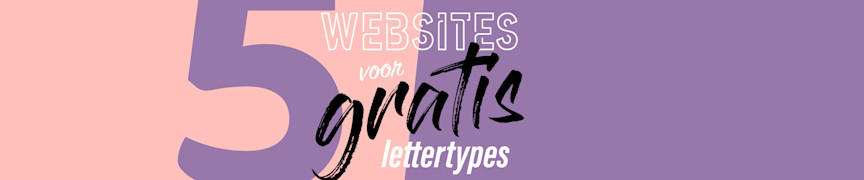
De vijf beste websites voor gratis fonts
Organiseer je een feest? Verkoop je een nieuw product? Heb je een knallende actie? Dan kunnen opvallende flyers of posters niet ontbreken. Terugkerend element op bijna elk stukje drukwerk is je lettertype. Daarom laten wij je in dit blog zien waar je de beste gratis fonts vandaan haalt.
Een font is net zo persoonlijk als je huisstijl of boodschap. Geef de keuze van een lettertype daarom net zoveel aandacht als de rest van je ontwerpproces.
Dafont.com
321-5xgratisfonts-dafont-featured Het fontwalhalla voor designers. Op moment van schrijven telt deze site maar liefst 34.472 fonts, in negen verschillende hoofdcategorieën. Allemaal gratis! Of je nou zoekt naar een nieuw font voor je website of een lettertype voor een nieuwe tattoo, er zit iets voor je tussen.
Google.com/fonts
321-5xgratisfonts-Googlefonts-featured Google is je vriend. Zoekt en gij zult vinden is kinderspel voor Google, ook voor je gratis fonts. Deze site is vooral handig voor webdesigners. De meeste fonts die je hier downloadt zijn web-proof.
Fontsquirrel.com
321-5xgratisfonts-FontSquirrel-featured Fontsquirrel is het schattige broertje van Dafont.com. Je kan er alleen iets meer doen dan alleen fonts downloaden. Op Fontsquirrel vind je een uitgebreid blog, een forum waar mensen elkaar helpen de juiste fonts te vinden en zelfs een font identifier.
Losttype.com
321-5xgratisfonts-Losttype-featured De verloren pareltjes onder de fonts vind je hier terug. Losttype publiceert niet vaak iets, maar als ze het doen plaatsen ze fantastische fonts. Mooie scriptfonts en eigentijds kleurgebruik, lekker van nu! Frisse fonts voor je meesterlijke menukaart of lekkere lettertypes voor op een T-shirt.
Behance.com
321-5xgratisfonts-Behance-featured Hét designersplatform! Een soort wereldwijd archief aan designerportfolio’s. Van fotografie tot aan ontwerpen voor woonhuizen, je vindt het allemaal op Behance.com. Fonts dus ook. Typ in de zoekbalk wat je nodig hebt en je vindt fantastisch werk.